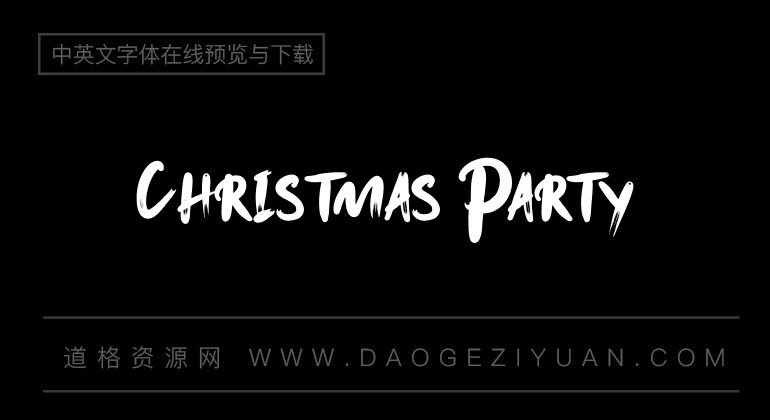
Christmas Party 字体是一种由粗体、斜体和楷体组成的复古字体,它具有浓厚的节日气息,适合用于节日海报、活动宣传、礼物标签等场景。字体的粗体部分有着凸起的线条,而斜体部分则带有更多的细节,给人以活泼可爱的感觉。此外,它的楷体部分则具有传统的节日气氛,能够给用户带来温馨的感觉。内容介绍
Christmas Party是一款非常不错的手写艺术字体,具有很好的视觉感,适合于文化类的宣传设计、商业类品牌的广告和产品包装设计以及个性化文字排版等较多场景。